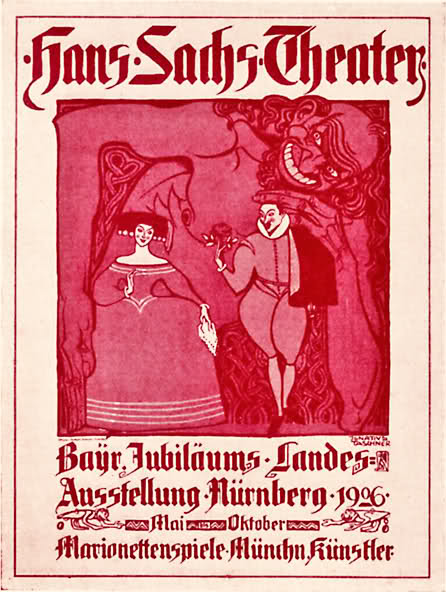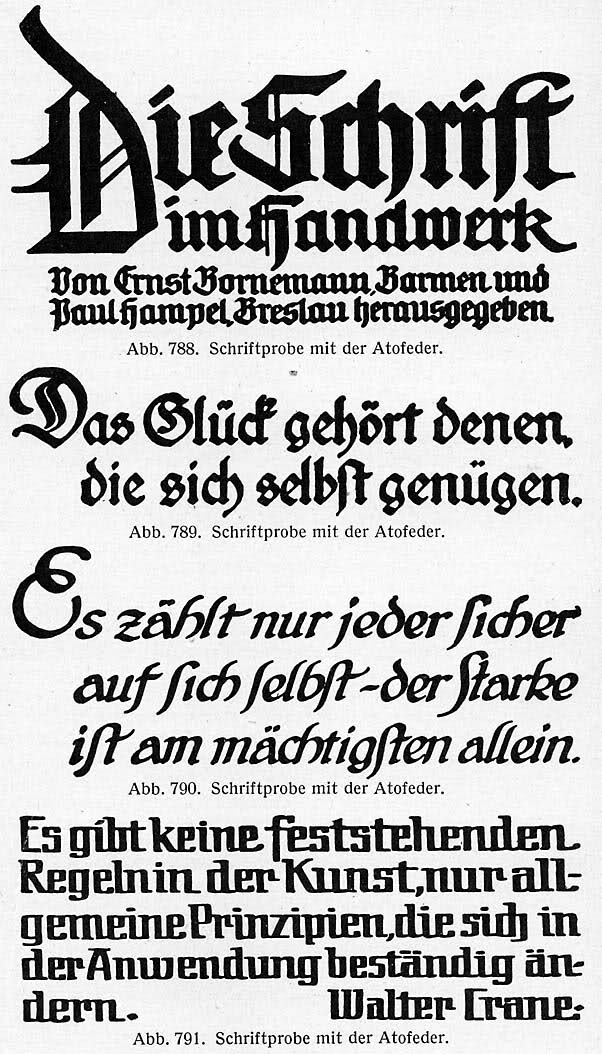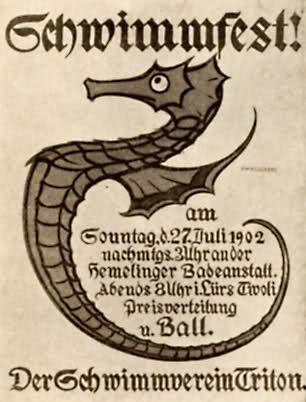
Historische Fraktur ohne langes ſ?
Heute wird ja (leider) beim Fraktursatz oft auf das lange ſ verzichtet was hier ja ausgiebig diskutiert wurde.
Nun findet man aber bisweilen auch ältere Anwendungen gebrochener Schriften auf dem man nur das runde s verwendet. Zuletzt wieder gesehen auf diesem Reservistenkrug welcher zu Beginn des 20. Jahrhunderts entstand und am Samstag in der Fernsehsendung „Kunst und Krempel“ besprochen wurde.
Heute verzichtet man ja nun bisweilen auf das lange ſ um die Lesbarkeit bei nicht an gebrochene Schriften gewohnte Leser zu erhöhen aber warum wurde dies damals so gehandhabt?
Bin gerade erst 24h wieder in Karlsruhe. War zuvor in Bremerhaven und dort war ich auch kurz über den Geestemünder Friedhof zum Gießen.
Dort fiel mir auf, dass auf den Grabsteinen mit Fraktur, auch denen, die laut jüngstem Datum schon paar Jahrzehnte auf dem Buckel haben könnte, nirgends ein langes s verwendet wurde. Einzige Ausnahme war ein Gedenkstein einer Vertriebenenorganisation oder so ... Vermutlich schlicht ein anderer Hersteller/bundesweiter Auftraggeber?
Ich habe zugegebenermaßen wohl erstmals auf einem Friedhof so genau auf das lange s geachtet, von daher weiß ich nicht,
- ob das ein allgemeine steinmetzspezifische Sache ist, die es auch anderswo gibt, oder
- ob das eine spezielle Geestemünder Steinmetzverschwörung gegen das lange s ist ...
Eigentlich wollte ich aufgrund des anderen Diskussionsfadens nachschauen, ob das lange s in letzter Zeit außer Gebrauch gerät, aber zumind. dort scheint es schon länger ausrangiert?
Vielleicht sollte ich mal einen Spaziergang über den Karlsruher machen ...
Jedenfalls hat's mich verwundert, zumal Grabsteine bei der Begründung des [sZ][/sZ] ja eine Rolle spielten ... Einführen des einen, ausrangieren des anderen ... Hmmm ... Also doch eine lokale Verschwörung? ;)
Also zumindest um 1920 herum war das ſ im Harzvorland in der Provinz Sachsen anscheinend noch üblich:
… warum wurde dies damals so gehandhabt?
Warum das so gehandhabt wurde, kann man nicht so einfach sagen. Das sind Konventionen, die sich über beträchtliche Zeiträume – auch unter Einfluss der Handschrift – entwickelt haben. Welche Faktoren da jeweils reingespielt haben, ist nicht so einfach zu (er)klären. Die Frakturfreunde haben zwar ein paar typische Parolen, warum Deutsch in Fraktursatz ſ und ganz bestimmte Zwangsverbünde bräuchte, aber die stimmen faktisch hinten und vorne nicht.
Jedenfalls hat's mich verwundert, zumal Grabsteine bei der Begründung des ẞ ja eine Rolle spielten ... Einführen des einen, ausrangieren des anderen ... Hmmm ... Also doch eine lokale Verschwörung? ;)
Eszett ist ein amtlicher Buchstabe des Alphabets in Deutschland und Österreich mit konkreter lautlicher Funktion. Das ſ ist nur ein Morphemgrenzen-Anzeiger. Das kann man (heute) überhaupt nicht auf eine Stufe stellen.
A) Der Produzent des Reservistenkrugs hat im Herstellungsprozess zur Beschriftung keramische Abziehbilder verwendet. Da ist ein rund-s wesentlich praktischer, wenn es um den fehlerfreien Transfer des Abziehbildes vom Trägerpapier auf den Keramikscherben geht.
und/oder
B) Der Produzent des Reservistenkrugs verwendete irgendeine Rotunda oder gotische Schrift, die nur das rund-s hat.
und/oder
C) Der Produzent des Reservistenkrugs war im damals heißen Fraktur-Antiqua-Streit auf Seiten der Antiquarianer, wollte es sich aber nicht mit der Kundschaft verderben. :-)
Und was die Namen auf dem Friedhof betrifft: Bei Namen ist es doch ohnehin ein eigen Ding mit der s-Anwendung. Und vielleicht haben die Hinterbliebenen das nicht so verbissen gesehen. Die waren schriftmäßig gebildeter als der heutige Durchschnittsdeutsche.
Dort fiel mir auf, dass auf den Grabsteinen mit Fraktur, auch denen, die laut jüngstem Datum schon paar Jahrzehnte auf dem Buckel haben könnte, nirgends ein langes s verwendet wurde.
Wieviel genau sind ein paar Jahrzehnte? Bei allem was jünger ist als 1950, fände ich ein Fehlen des ſ nicht allzu ungewöhnlich.
B) Der Produzent des Reservistenkrugs verwendete irgendeine Rotunda oder gotische Schrift, die nur das rund-s hat.
Dass die Schriften über kein ſ verfügen, kann ich zwar nicht ausschließen, aber es sind zumindest teilweise Frakturen und keine Rotunda.
C) Der Produzent des Reservistenkrugs war im damals heißen Fraktur-Antiqua-Streit auf Seiten der Antiquarianer, wollte es sich aber nicht mit der Kundschaft verderben. :-)
Da der Herstellerverweis die einzige im Beitrag sichtbare Stelle ist, in der ein ſ verwendet wird, würde ich das ausschließen.
Ich habe schon eine ganze Menge historischer gebrochener Schriften gesehen, aber eigentlich immer mit Verwendung des ſ, weswegen ich den Krug schon ungewöhnlich finde. Das ist in etwa so, als hätte jemand 1980 die neue Rechtschreibung verwendet.
Mit „Parolen“ habe ich markige Sprüche gemeint, denen ganz oder teilweise eine sachliche Grundlage fehlt. Zum Teil mögen diese nicht ganz richtigen Behauptungen auf Glauben beruhen, zum Teil mögen Sie auch absichtlich falsch sein, um die eigene Sache zu fördern. Solche Sprüche gibt es auf beiden Seiten.